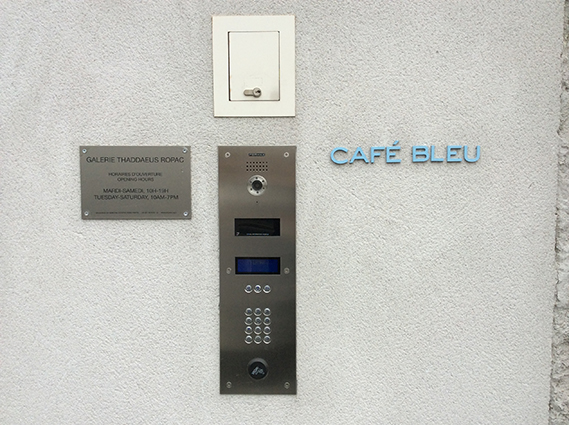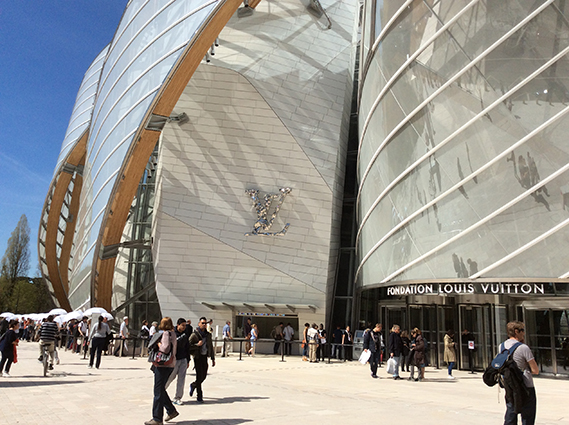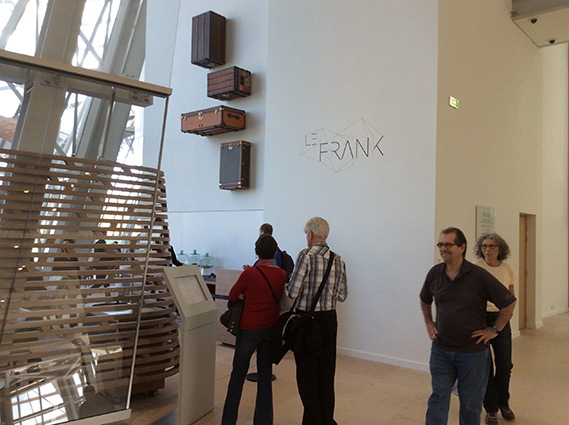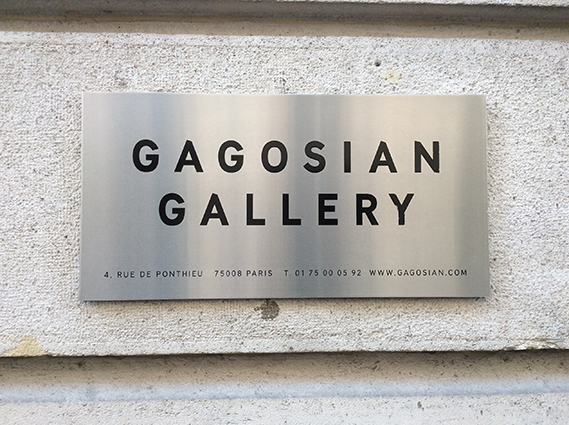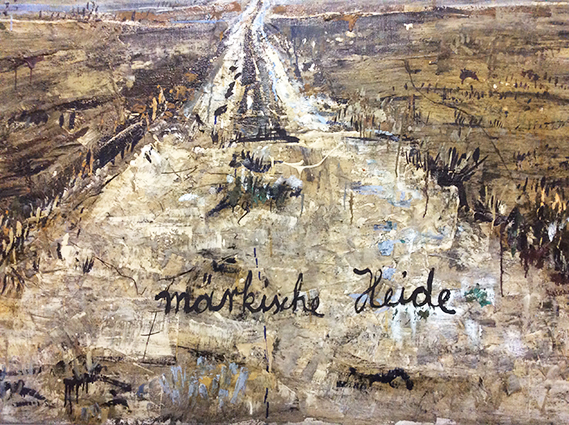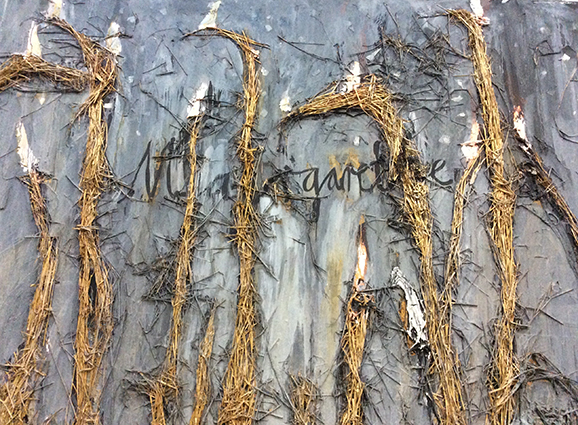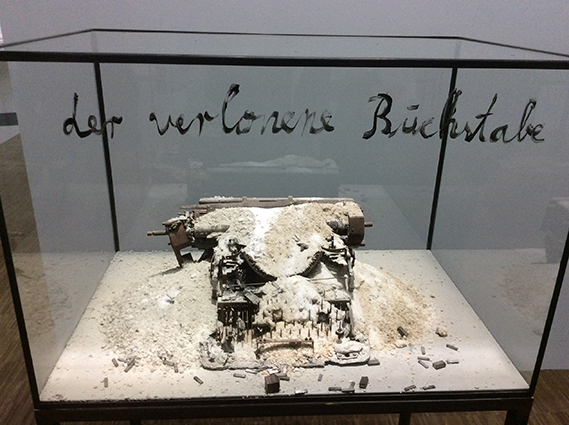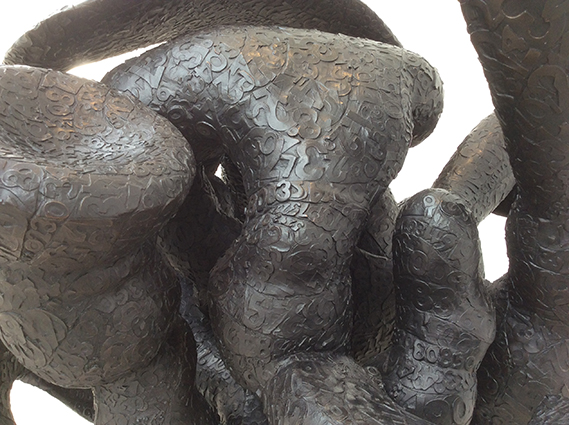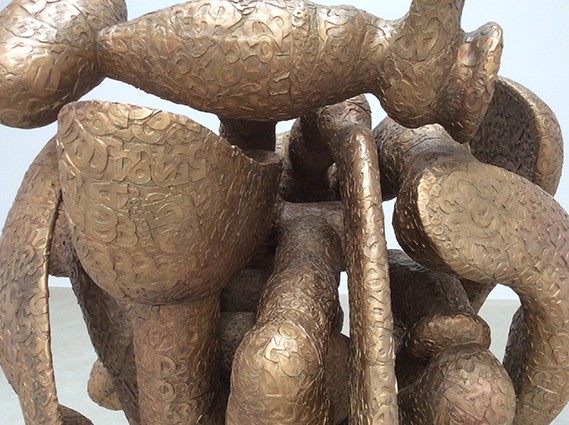
PARIZ
Pažnja koja se posvećuje vizuelnom u Parizu ogleda se, između ostalog, u dizajnerskim rešenjima koja se opažaju na objektima najrazličitijih namena, vrsta i statusa u javnom prostoru. Sveobuhvatan dizajn i planiranje načina na koji će se oni vizuelno reprezentovati podrazumeva i kreiranje jedinstvenih identiteta i posebnih slovnih rešenja. Istovremeno, onima koji svojim istreniranim okom najpre registruju slova, a zatim i sve ostalo, podjednako podsticajno polje mogu predstavljati izložbe, na kojima se često mogu videti radovi umetnika koji su pismo i tipografiju tretirali kao sredstvo umetničkog izražavanja i upotrebljavali ih na nekonvencionalne načine.
U aprilu 2016. još uvek je mogla da se vidi velika retrospektiva Anselma Kifera (Anselm Kiefer) u Centru Pompidu, čija dela su interesantna i zbog primene pisma, budući je ovaj umetnik prepoznatljiv po rečima koje ispisuje na svojim slikama, kontekstualizujući ih na taj način. U istom muzeju početkom aprila otvorena je prva velika retrospektiva Paula Klea (Paul Klee) u Francuskoj nakon 1969. godine. Izložba je obuhvatila preko 250 dela, među kojima se nalaze i ona koja inkorporiraju slova, što je jedna od osobenosti ovog umetnika. Istovremeno, u Galeriji Tadeuš Ropak (Thaddaeus Ropac) u predgrađu Pantan, postavljena je izložba monumentalnih skulptura Tonija Krega (Tony Cragg), koji je poseban i po tome što upotrebom nekonvencionalnih materijala i oblika ispituje mogućnosti fakture svojih skulptura. O tome svedoči i nekoliko izloženih radova koji imaju prepoznatljive „kregovske“ biomorfne oblike, ali čija površina je na kreativan način tretirana umnoženim brojkama. Jedan od velikih umetničkih događaja bila je retrospektiva španskog umetnika Mikela Barsela (Miquel Barceló), koja je organizovana u Muzeju Pikaso i Nacionalnoj biblioteci Francuske. Prvi put od kada je ovaj muzej otvoren, pozvan je jedan savremeni umetnik da izloži dela, sa ciljem uspostavljanja svojevrsnog dijaloga sa Pikasovim radovima. S druge strane, Barselova postavka u Nacionalnoj biblioteci Francuske, u kojoj dominiraju grafike, posebno je interesantna zbog velike instalacije na prozorima biblioteke u vidu monumentalnog crteža rađenog u glini kojom je staklo premazano. U kontekstu pisma, interesantni su dnevnici u kojima je umetnik beležio svoje doživljaje, kao i tok rada, na putovanjima po Africi i drugim krajevima sveta.
Pariske ulice pružaju mogućnost da se oseti i doživi atmosfera grada i njegov ritam, dok usput mogu da se vide različiti primeri grafičkog oblikovanja vizuelnih identiteta. Kao zabavna podvrsta mogu se izdvojiti specijalizovane poslastičarnice poznatih francuskih kuvara, kao što su Žak Ženan (Jacques Genin), Kristof Adam (Christophe Adam) ili Kristof Mišalak (Christophe Michalak). Ne samo što njihove jestive kreacije odražavaju sofisticiranost i individualni pristup, već su i prostori i logotipi njihovih radnji osmišljeni na atraktivan način. Ovakve radnje samo su neki od brojnih primera prodavnica različitih namena, čiji natpisi se kreću od rafiniranih do onih neformalnijih, dok je često moguće videti primere ad hoc inventivnosti zaposlenih koji na duhovite načine kreiraju natpise u izlozima koji su najčešće rukom ispisani. Dok veliki broj ovakvih mesta pokazuje entuzijazam vlasnika da izgrade poseban identitet, ukazujući istovremeno na koje načine tipografija i pismo mogu da dožive svoju transformaciju i razvoj u javnom prostoru, primeri sa izložbi, naizgled antipodno, svedoče o njihovoj primeni i poimanju u radovima likovnih umetnika.